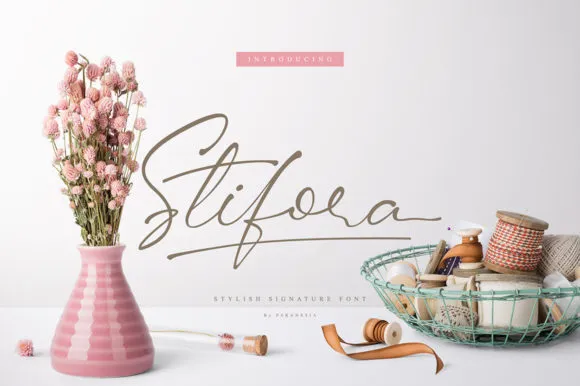
Stifora Script Font – Fonte Grátis
Stifora Script Font
A fonte Stifora Script é uma escolha perfeita para quem busca criar designs com um toque romântico e sofisticado. Introduzida pelo designer Paranesia, esta moderna fonte de script vem inspirada na autêntica mão escrita, oferecendo um brilho luxuoso para seus projetos. Seja ela uma assinatura elegante, um toque de fotografia única, capas de revistas sofisticadas ou até mesmo rótulos criativos para roupas e cards de visita, Stifora traz consigo o ar de uma autêntica escrita à mão que faz seu trabalho. Perfeita tanto para estilização de títulos quanto para criação de logotipos e marcas, Stifora é uma fonte script ideal para todos aqueles desejando dar um toque pessoal em seus designs. Quebre o código de sigilo e descubra a magia da autêntica escrita à mão com Stifora Script.